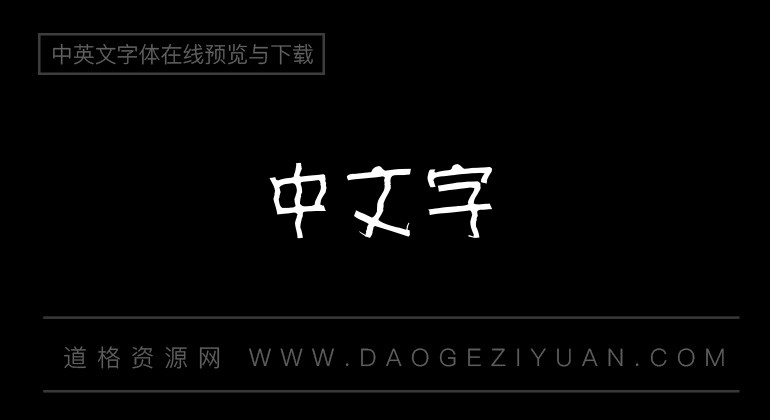
万用波纹体
万用波纹体是一种特殊的字体,它使用一种特殊的线条绘制字体,使得字体看起来有点像波浪线一样。它的特点是字体的形状可以根据文本大小自动调整,从而使文本看起来更加美观。万用波纹体通常用于设计师创作美丽的文字,以及创建标题和标识。它还可以用于创建精美的拼图,以及设计印刷品和网页等。
万用波纹体是一款非常不错的手写艺术字体,具有很好的视觉感,适合于文化类的宣传设计、商业类品牌的广告和产品包装设计以及个性化文字排版等较多场景。